싸인은 단순한 서명이 아니라 자신을 표현하는 중요한 요소예요. 멋지고 개성 있는 싸인을 만들면 브랜드 아이덴티티가 될 수도 있고, 신뢰감을 줄 수도 있어요. ✅
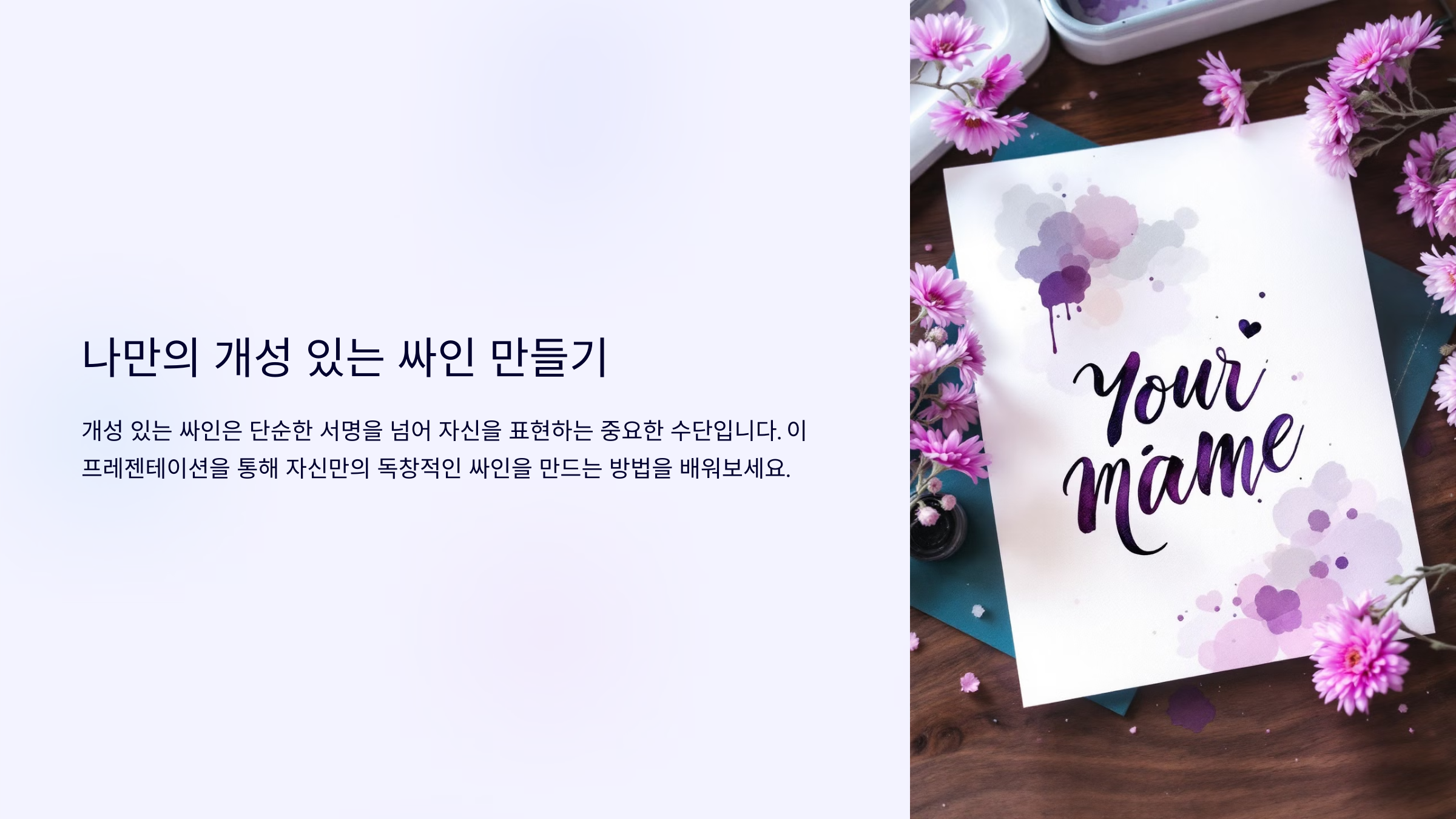
내가 생각했을 때, 싸인은 빠르게 쓸 수 있으면서도 강렬한 인상을 주는 것이 가장 좋아요. 너무 복잡하면 불편하고, 너무 단순하면 개성이 없을 수도 있어요. 이제 나만의 개성 있는 싸인을 쉽게 만들어볼까요? ✍
개성 있는 싸인의 중요성 💡
싸인은 단순한 이름이 아니라 자신의 브랜드를 표현하는 중요한 도구예요. 멋지고 개성 있는 싸인은 기억에 남을 뿐만 아니라, 신뢰도를 높이는 효과도 있어요. ✅
🔹 싸인은 왜 중요할까? - 서명은 본인 확인의 역할을 해요. - 비즈니스에서 프로페셔널한 이미지를 줄 수 있어요. - 연예인, 크리에이터는 자신만의 브랜드를 구축할 수 있어요.
🔹 좋은 싸인의 조건
✅ 빠르게 쓸 수 있어야 함
✅ 단순하면서도 개성이 있어야 함
✅ 일관성을 유지해야 함
📌 개성 있는 싸인의 필요성 🔍
요소 설명 신뢰도 공문서나 계약서에서 본인을 증명하는 역할 브랜드화 연예인, 아티스트, 크리에이터의 브랜드 요소 기억에 남음 팬이나 고객들에게 강렬한 인상을 남길 수 있음 개성 표현 한눈에 알아볼 수 있는 나만의 스타일 만들기 이제 싸인 스타일을 정하는 방법을 살펴볼까요? ✨
싸인 스타일 정하기 ✨
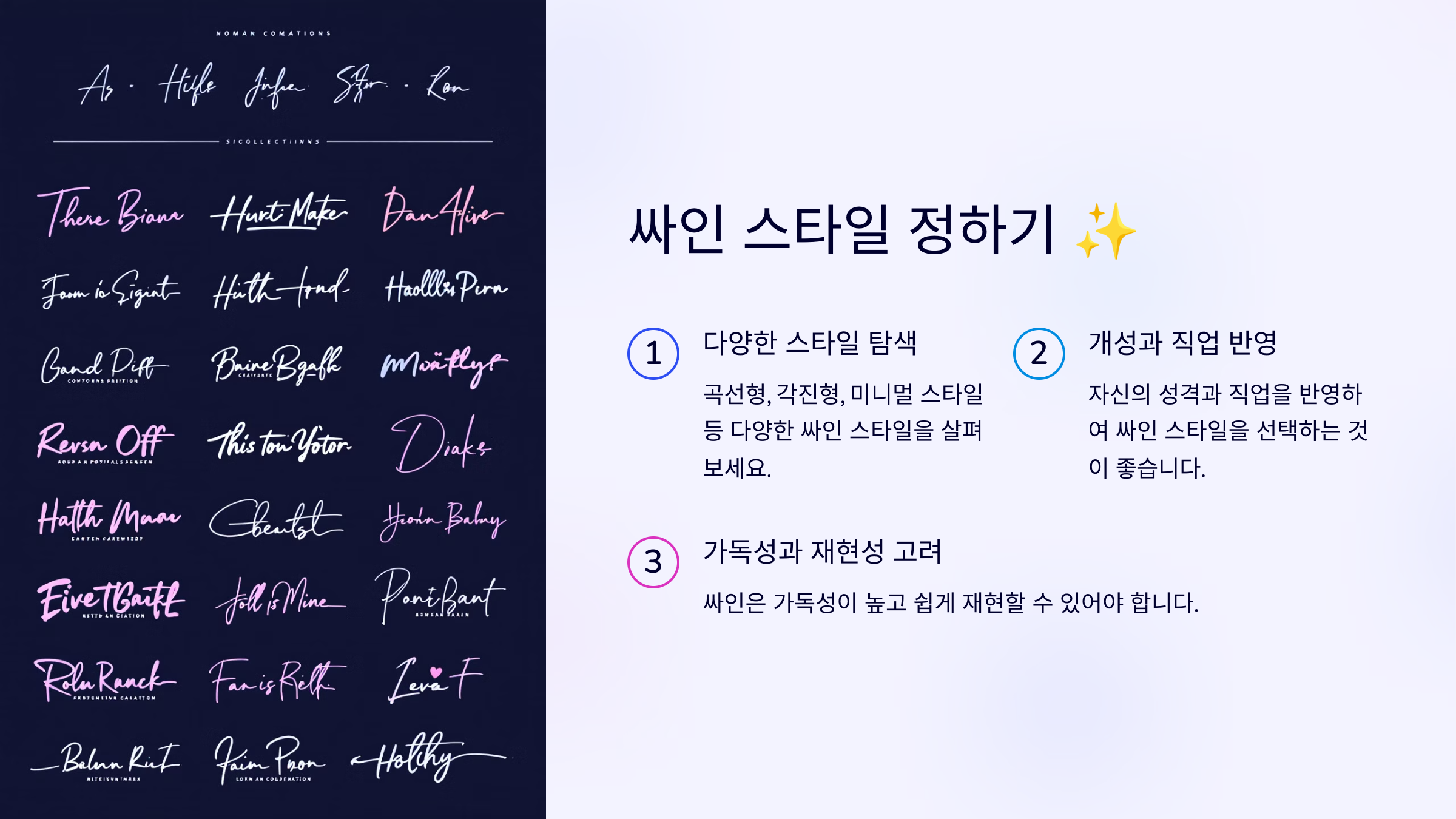
싸인을 만들기 전에 어떤 스타일로 할지 정하는 것이 중요해요. 개인 브랜드를 강조할 것인지, 빠르고 실용적인 싸인을 만들 것인지 먼저 결정해보세요! 🎯
🔹 대표적인 싸인 스타일
1. 이니셜형 – 짧고 간결한 싸인 (예: J.K, T.S)
2. 필기체형 – 자연스럽고 부드러운 흐름 (예: Taylor Swift 스타일)
3. 기호형 – 하트, 별, 번개 등 개성 있는 심볼 추가
4. 그래픽형 – 싸인에 작은 그림 요소 추가 (예: G-Dragon 스타일)
📌 싸인 스타일 비교 분석 🖊
스타일 특징 추천 대상 이니셜형 짧고 강렬한 인상, 빠르게 서명 가능 비즈니스 전문가, 공문서 서명 필기체형 부드럽고 우아한 흐름, 자연스러움 예술가, 디자이너, 작가 기호형 별⭐, 하트❤, 번개⚡ 같은 기호 포함 연예인, 크리에이터, 개성 강조 그래픽형 싸인 속에 그림 요소 포함 아티스트, 인플루언서, 유튜버 이제 기본적인 필기체 연습법을 배워볼까요? 🖊
간단한 필기체 연습법 🖊
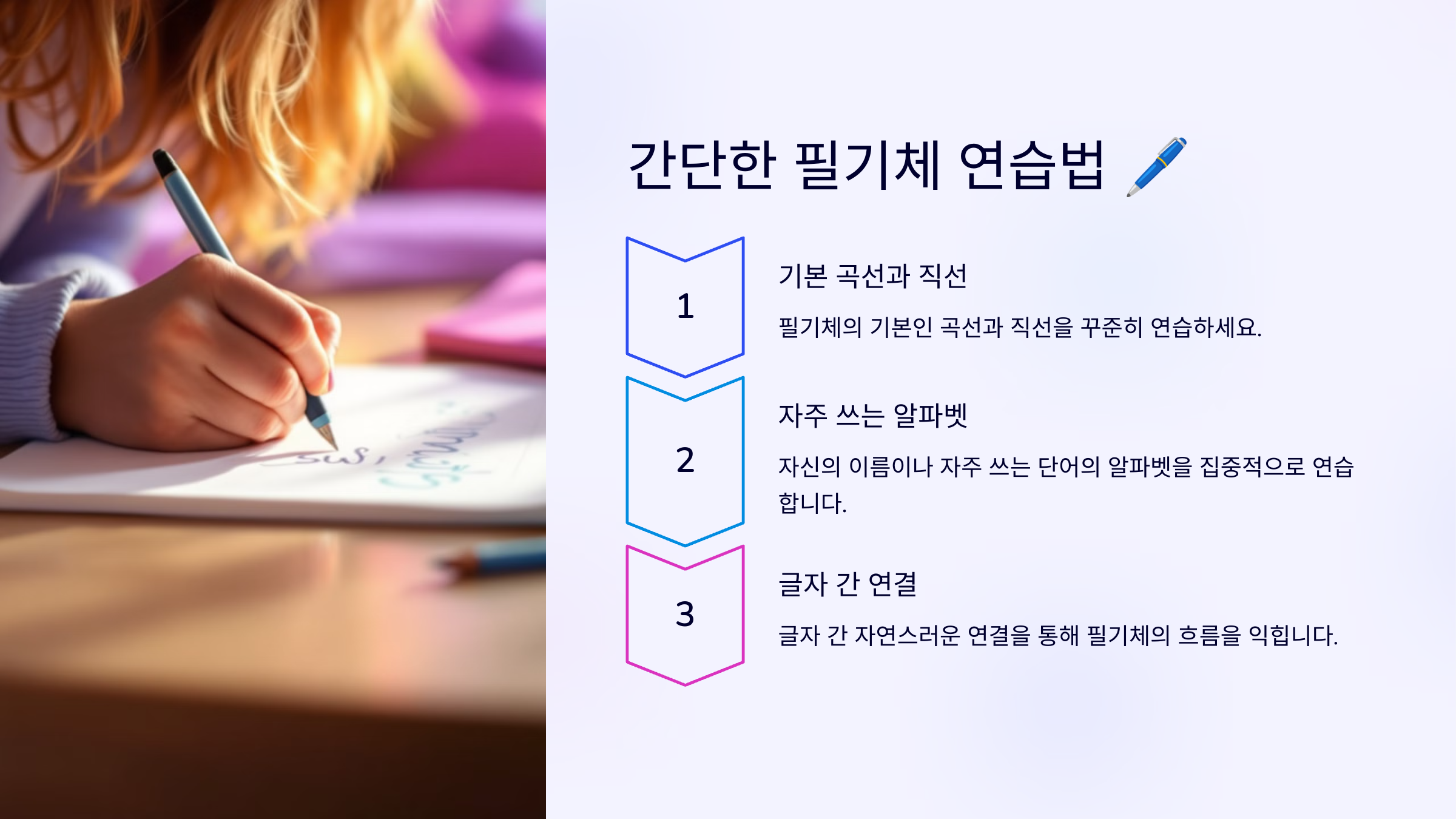
싸인을 부드럽고 자연스럽게 만들려면 필기체 스타일을 연습하는 것이 좋아요. 필기체는 흐름이 자연스럽고, 빠르게 싸인하기에 적합한 스타일이에요. ✍
🔹 필기체 연습 방법
1. 손목의 힘을 빼고 부드럽게 써보기
2. 글자 간격을 일정하게 유지하기
3. 알파벳 또는 한글을 자연스럽게 연결하기
4. 같은 단어를 반복해서 써보면서 흐름 익히기
📌 필기체 연습을 위한 핵심 요소 ✨
연습 방법 설명 손목의 힘 빼기 부드러운 곡선을 만들기 위해 손목의 긴장을 풀기 글자 간격 조절 한 글자씩 일정한 간격 유지 연결선 활용 글자 간 부드러운 연결로 자연스러움 강조 반복 연습 같은 단어를 여러 번 써보며 감각 익히기 이제 이니셜을 활용한 싸인 만들기 방법을 배워볼까요? 🔤
이니셜을 활용한 싸인 만들기 🔤
이니셜 싸인은 간결하면서도 강렬한 인상을 남길 수 있는 스타일이에요. 특히 빠르게 싸인해야 하는 비즈니스 환경이나 공문서 서명에 적합해요. ✅
🔹 이니셜 싸인 만드는 방법
1. 이름의 첫 글자만 활용 (예: J.K, T.S)
2. 이니셜을 곡선이나 직선으로 변형
3. 이니셜을 연결해서 필기체 느낌으로 만들기
4. 마지막에 포인트 기호(⭐, ⚡, ❤ 등) 추가 가능
📌 이니셜 싸인 스타일 분석 ✍
스타일 특징 추천 대상 이니셜 단순형 J.K, T.S처럼 짧고 간결한 스타일 비즈니스, 공문서 서명 이니셜 필기체형 이니셜을 자연스럽게 연결하여 부드러운 흐름 예술가, 디자이너, 크리에이터 이니셜 + 기호형 ⭐, ⚡, ❤ 같은 기호 추가하여 개성 강조 연예인, 인플루언서, 크리에이터 이제 싸인에 개성을 추가하는 방법을 알아볼까요? 🎨
싸인에 개성 추가하는 방법 🎨
싸인을 더 특별하게 만들고 싶다면 작은 요소만 추가해도 개성이 확 달라질 수 있어요. 너무 복잡하지 않으면서도 나만의 스타일을 살리는 것이 중요해요! ✨
🔹 싸인에 개성 추가하는 방법
1. 기호(⭐, ❤, ⚡, ☁ 등) 추가하기
2. 글자의 크기 조절 (첫 글자 강조)
3. 싸인의 끝부분에 곡선 또는 직선 포인트 추가
4. 자신만의 독특한 패턴 만들기
📌 싸인을 더 개성 있게 만드는 요소 🖊
추가 요소 설명 기호 추가 ⭐, ❤ 같은 아이콘을 싸인에 포함 크기 조절 첫 글자를 크게 쓰거나 비율 조정 마무리 선 싸인의 끝을 직선 또는 곡선으로 마무리 특별한 패턴 자신만의 스타일을 유지하는 독창적인 디자인 이제 완성된 싸인을 연습하는 방법을 알아볼까요? 🚀
완성된 싸인 연습법 🚀
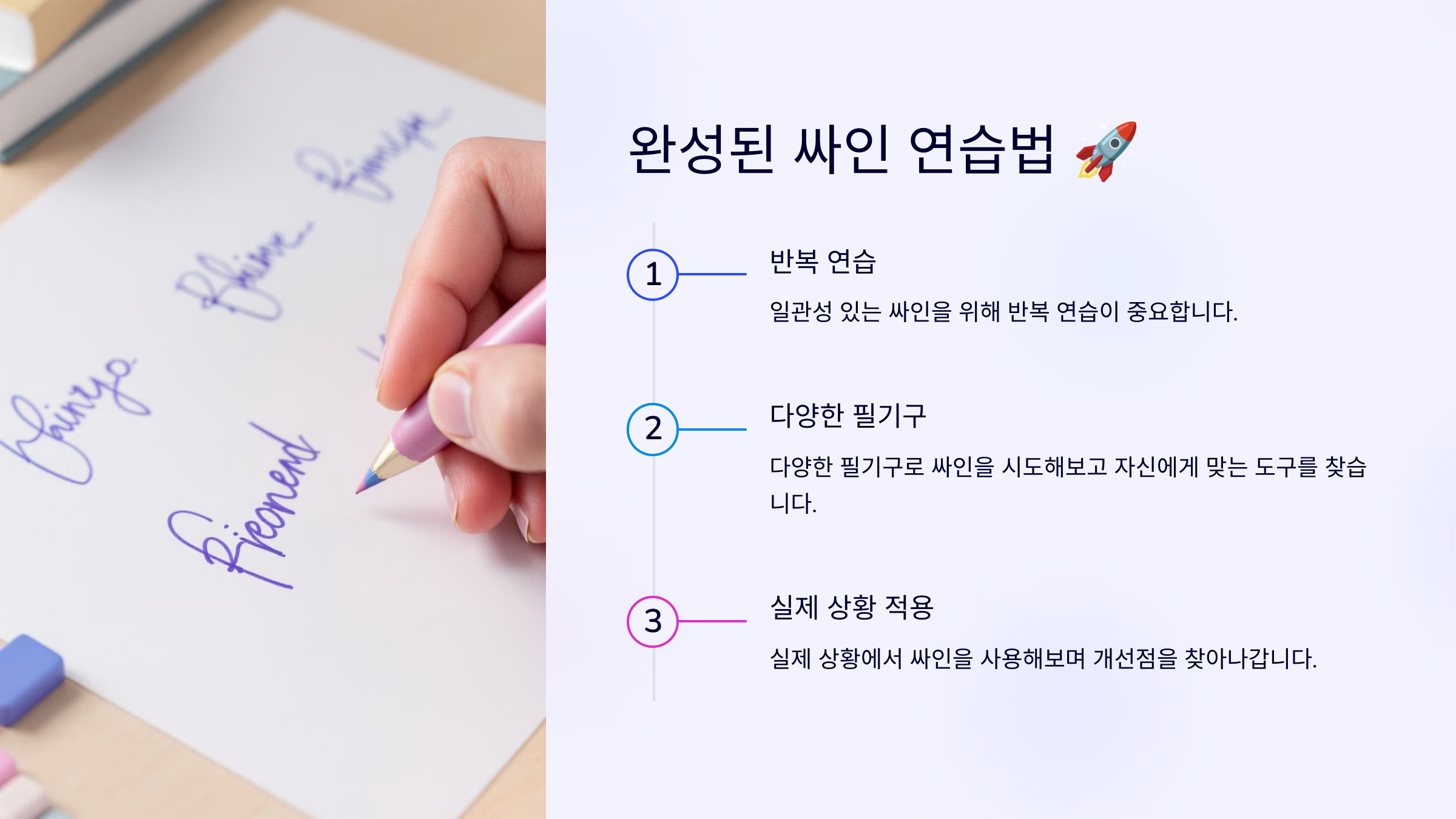
싸인을 만들었다면, 이제 꾸준한 연습을 통해 손에 익히는 과정이 필요해요. 싸인을 할 때마다 모양이 달라지지 않도록 일관성을 유지하는 것이 중요해요! 🖊
🔹 싸인 연습 방법
1. 눈 감고 싸인 연습하기 (손의 감각 익히기)
2. 다양한 크기로 싸인 연습 (A4, 명함, 포스트잇)
3. 빠른 속도로 싸인 연습 (5초 이내에 완성 목표)
4. 거울을 보며 싸인 확인하기 (다른 사람이 볼 때 느낌 체크)
📌 싸인을 효과적으로 연습하는 방법 ✍
연습 방법 설명 눈 감고 연습 손이 기억하도록 반복 연습 다양한 크기로 연습 A4, 명함, 포스트잇 등 다양한 크기 테스트 빠른 속도로 연습 5초 이내에 싸인할 수 있도록 속도 조절 거울 확인 다른 사람이 봤을 때의 느낌 체크 이제 싸인에 대한 궁금증을 해결할 시간! FAQ에서 자주 묻는 질문을 정리해볼까요? ❓
FAQ ❓
Q1. 싸인을 만들 때 가장 중요한 요소는 무엇인가요?
A1. 싸인은 일관성, 속도, 가독성, 개성이 중요해요. 너무 복잡하면 빠르게 쓰기 어렵고, 너무 단순하면 개성이 부족할 수 있어요. 간결하면서도 나만의 스타일을 반영하는 것이 좋아요! ✍
Q2. 싸인의 크기는 어느 정도가 적당한가요?
A2. 싸인은 너무 크면 문서에서 공간을 많이 차지하고, 너무 작으면 가독성이 떨어질 수 있어요. A4 용지, 명함, 포스트잇 등 다양한 크기로 테스트하면서 적절한 크기를 찾는 것이 좋아요. 📏
Q3. 싸인을 바꾸면 법적 문제가 생길 수도 있나요?
A3. 법적으로 인정되는 문서에서는 기존 싸인과 다르면 문제가 될 수도 있어요. 따라서 한 가지 싸인을 정해 꾸준히 사용하는 것이 중요해요. 만약 싸인을 변경할 경우, 은행이나 공공기관에 미리 등록된 싸인을 업데이트해야 해요. ✅
Q4. 싸인에 기호(하트, 별 등)를 넣어도 괜찮을까요?
A4. 네! 기호를 넣으면 개성이 강조되고, 더욱 기억에 남는 싸인이 될 수 있어요. 하지만 너무 많은 기호를 넣으면 복잡해 보일 수 있으니 적절히 활용하는 것이 좋아요. ⭐❤⚡
Q5. 싸인 연습을 효과적으로 하는 방법이 있을까요?
A5. 반복적인 연습이 필수예요! 먼저 원하는 스타일을 정한 후, 1) 눈 감고 써보기 2) 다양한 크기로 연습하기 3) 빠른 속도로 써보기 이런 방식으로 연습하면 자연스럽고 멋진 싸인을 만들 수 있어요. 🚀
Q6. 싸인을 디지털 파일로 저장하는 방법은?
A6. 태블릿이나 스마트폰에서 스타일러스 펜을 이용해 싸인을 작성한 후 PNG 파일로 저장하면 활용할 수 있어요. Adobe Sign, DocuSign 같은 전자 서명 도구도 유용해요. 💻
Q7. 한글 싸인과 영어 싸인 중 어떤 것이 더 좋을까요?
A7. 사용 목적에 따라 달라요. - 한글 싸인: 독창적인 느낌을 줄 수 있어요. - 영어 싸인: 글로벌한 이미지와 간결한 디자인을 만들기 좋아요. 본인의 필요에 따라 선택하는 것이 가장 좋아요! ✅
Q8. 싸인을 바꾸면 운이 바뀐다는 말이 있던데, 사실인가요?
A8. 과학적인 근거는 없지만, 싸인을 바꾸면 자신감과 이미지가 달라지는 효과가 있어요. 특히, 성공한 사람들의 싸인을 보면 개성이 뚜렷한 경우가 많아요. 💯
이제 싸인 만들 때 실수하지 않고, 완벽한 나만의 싸인을 완성할 수 있겠죠? 🚀 꾸준히 연습해서 멋진 싸인을 만들어보세요! ✨